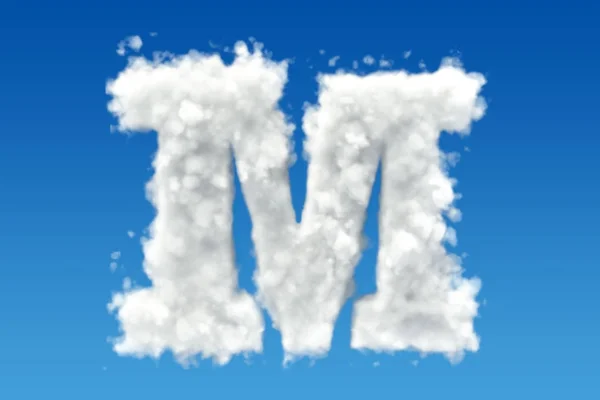
Пасмурное небо
Пасмурное небо от KC Fonts поставляется с полным набором алфавитов. Этот жирный шрифт предназначен только для личного использования. Он острый и сильный, попробуйте.